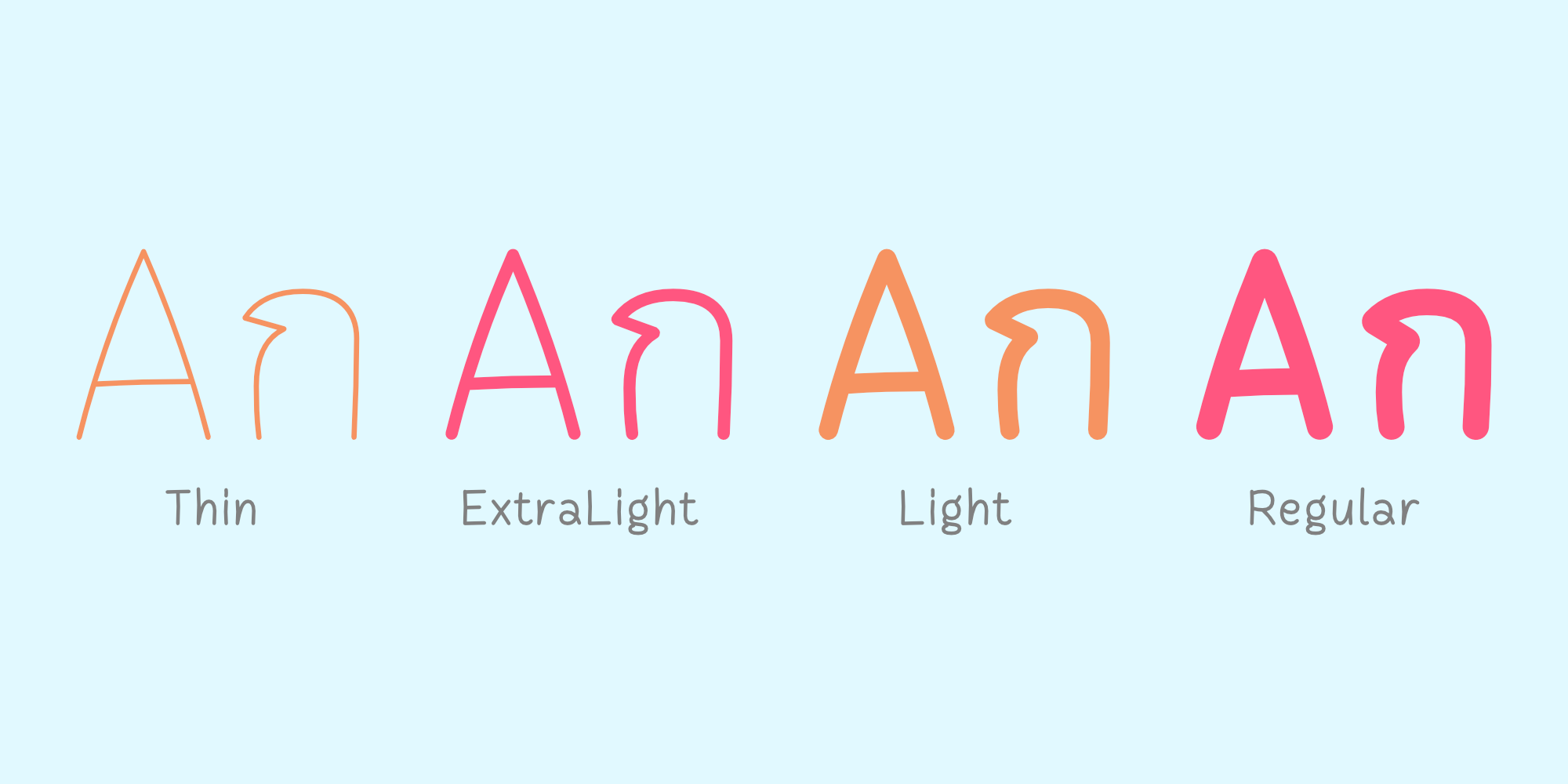
อนุบาล | Anuban
ชื่อฟอนต์ : อนุบาล | Anuban
Anuban เป็นแบบอักษรที่ออกแบบมาให้มีลักษณะคล้ายลายมือ โดยแทนที่จะใช้การเขียนด้วยมือจริง แบบอักษรนี้ถูกสร้างขึ้นด้วยเครื่องมืออย่าง pen tool ผลลัพธ์ของแบบอักษรนี้ให้ความรู้สึกเหมือนการคัดลายมือของเด็กอนุบาลที่คงความเป็นระเบียบเอาไว้ ฟอนต์นี้มี 8 รูปแบบ ซึ่งครอบคลุมน้ำหนักเส้นบางที่สุดจนถึงเส้นตัวปกติ และรองรับทั้งอักษรลาติน 1 และอักษรไทย ฟอนต์ Anuban เหมาะสำหรับการใช้งานในสื่อประชาสัมพันะธ์ที่ต้องการสื่อถึงความเป็นกันเอง ไม่เป็นทางการ และผ่อนคลาย เช่น งานออกแบบสำหรับเด็ก โปสเตอร์ การ์ด หรือสื่อประชาสัมพันธ์ที่ต้องการความรู้สึกนุ่มนวลและเป็นมิตร